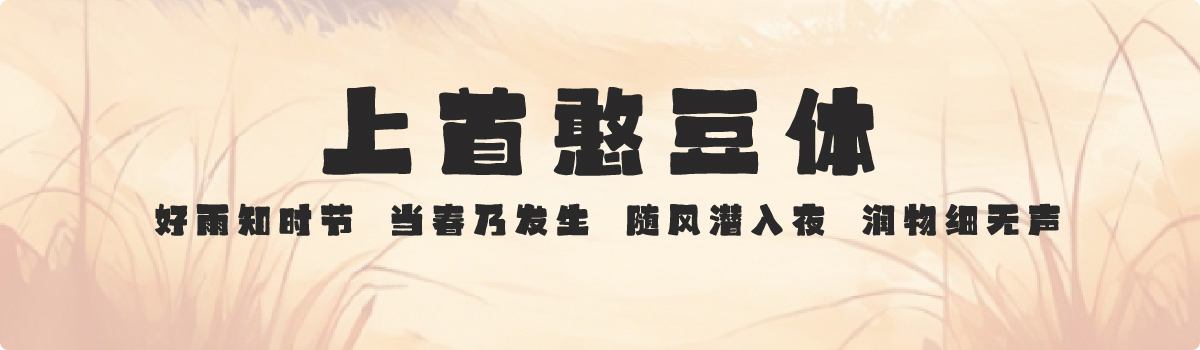
上首憨豆体
上首憨豆体,这款字体结构工整、笔画清晰,兼顾美观与易读性,适用于标题、正文、海报、包装、LOGO 等多种场景。字形优雅稳定,风格百搭耐看,适配日常排版与创意设计,让文字呈现更舒适、更具质感。上首憨豆体一笔一画,皆是细节,以均衡的比例、流畅的线条打造舒适视觉体验,字形端正大气,风格简约现代。无论是商业设计、品牌宣传还是日常排版,都能轻松驾驭,让文字更有格调与力量。上首憨豆体字体下载。